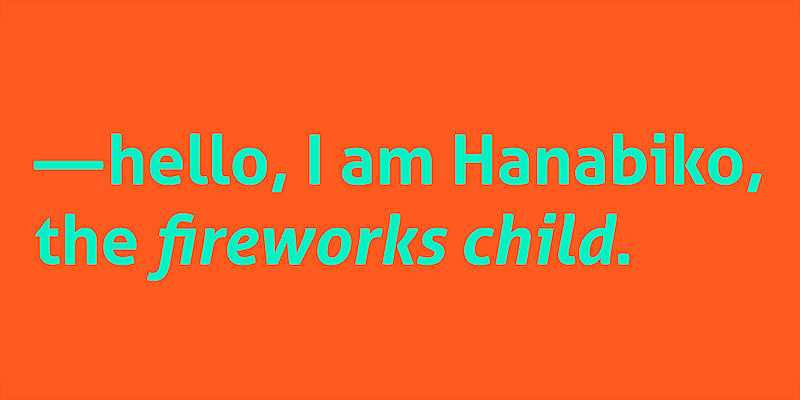
Aller Display führt das Design von Aller in eine etwas extremere Richtung und verwendet Kapitälchen für einige Kleinbuchstaben. Dies verleiht Ihrer Botschaft mehr Wirkung und einen hohen Wiedererkennungswert.